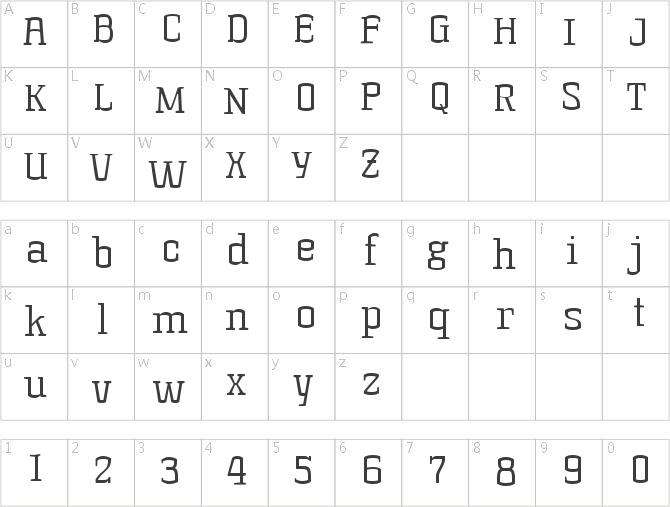
字体名称: Korneub
KorneuburgSlabLight-Light
KorneuburgSlabLight-Light介绍
KorneuburgSlabLight-Light字体字库是一款让人赏心悦目、百看不厌的英文字体,适合各类广告和产品包装设计应用,字体大小0.05MB,格式为ttf字体,上传用户是/zyj【GF】,作者/版权方为未知